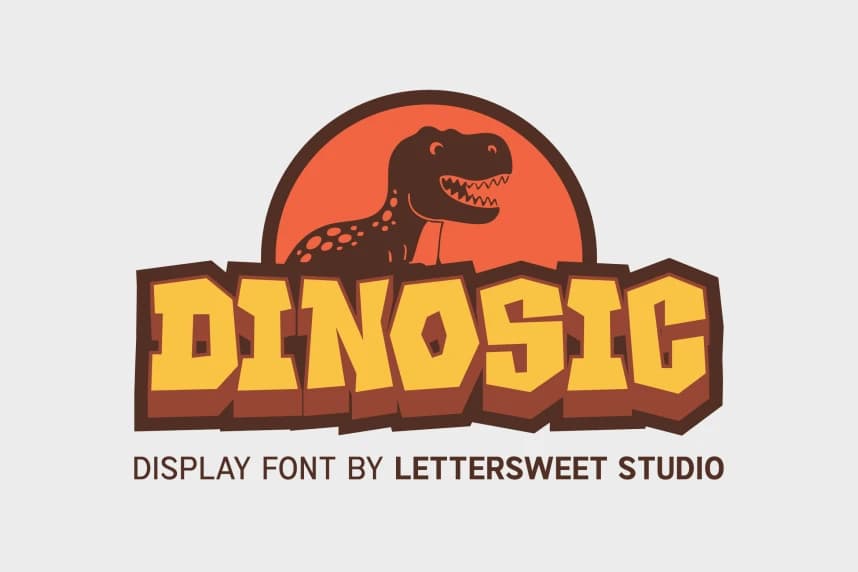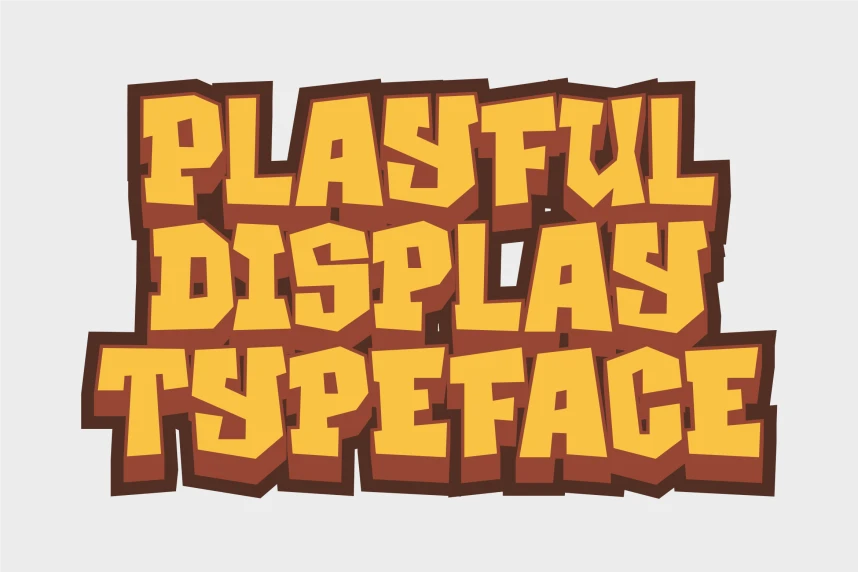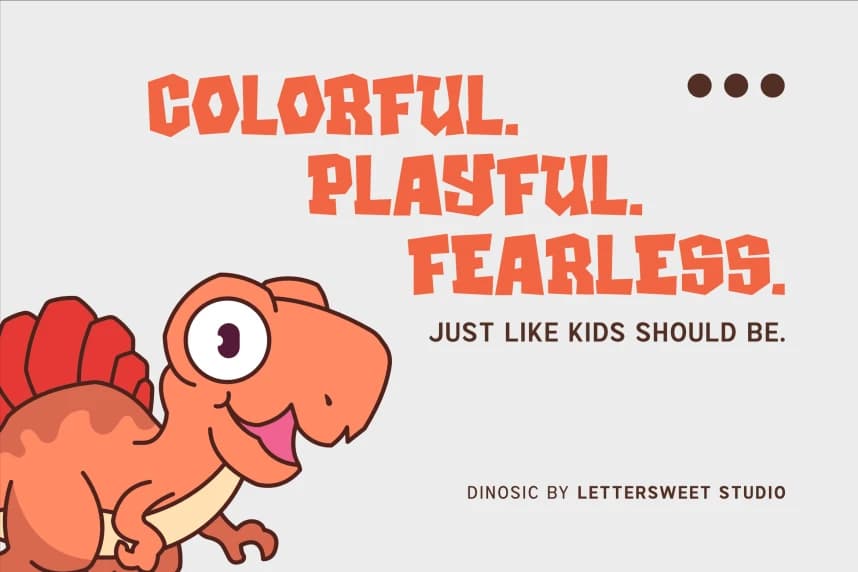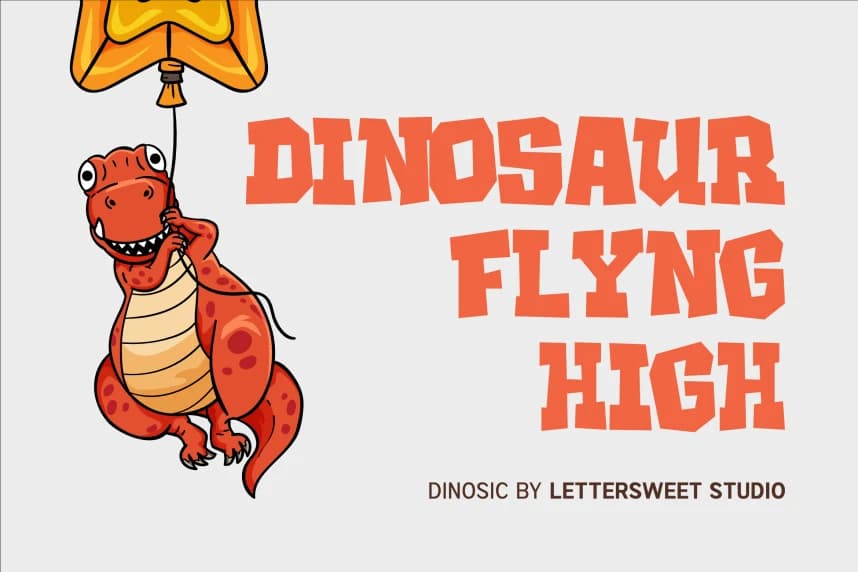
Dinosic Font
DINOSIC Font, dinozorların vahşi enerjisinden ve macera temalarından ilham alan cesur ve eğlenceli bir gösteri yazı tipidir. Kalın hatları, belirgin konturları ve eğlenceli kişiliğiyle DINOSIC, dikkati hemen çekmek üzere tasarlanmıştır. Merhaba, Lettersweet Studio'dan fontu indirdiğiniz için teşekkü
DINOSIC Font, dinozorların vahşi enerjisinden ve macera temalarından ilham alan cesur ve eğlenceli bir gösterim yazı tipi. Kalın şekilleri, belirgin hatları ve eğlenceli kişiliği ile DINOSIC, dikkati anında çekmek için tasarlandı. Merhaba, Lettersweet Studio'dan fontu indirdiğiniz için teşekkür ederiz.